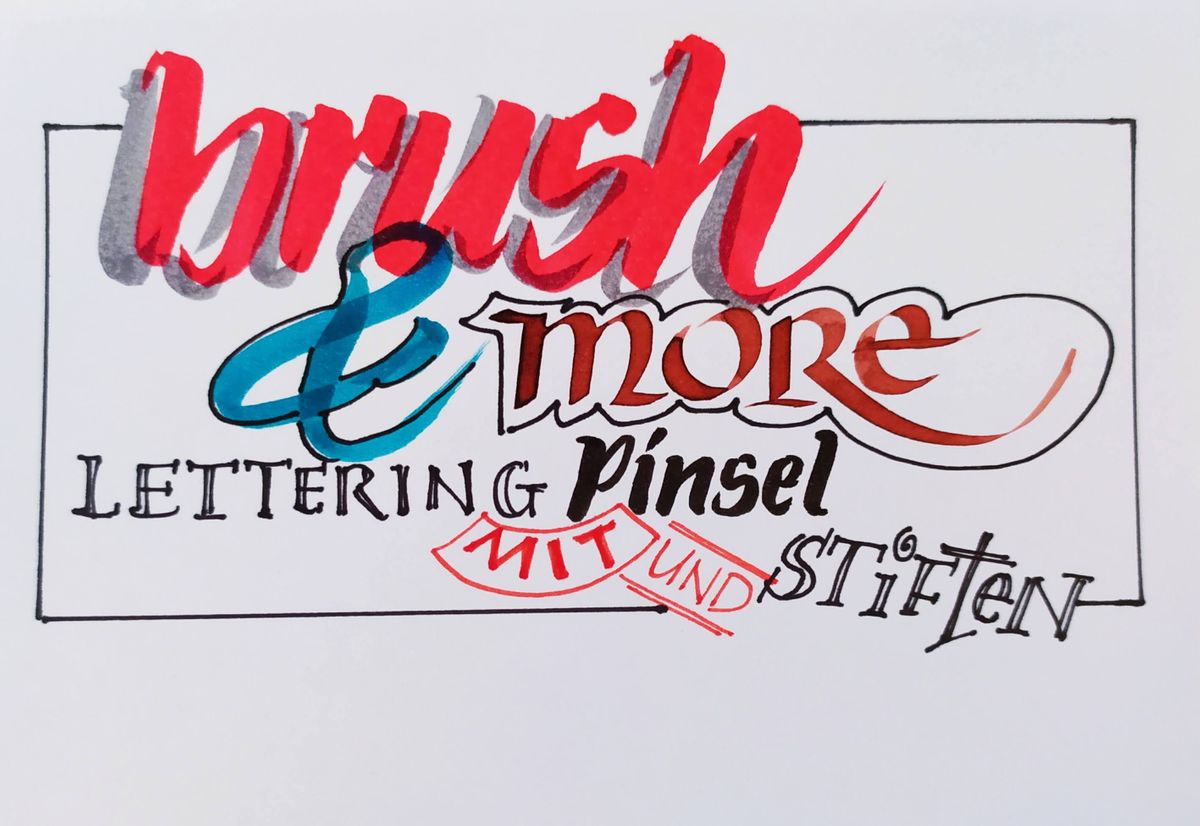
Besonders bei den geschwungenen schriftarten gibt es viele buchstaben in unzähligen varianten. Das klingt etwas nach vokabeln lernen und genau so ist es auch.
Kalligraphie schriftarten lernen. Bereits vor jahrhunderten gab sie der menschheit weltweit die. Dazu ist es wichtig nicht nur die striche und linienstärken genau zu studieren sondern auch die reihenfolge der strichführung zu beachten. Die oben beschriebenen werkzeuge und materialien reichen aus um sich erst einmal in die kunst des schönen schreibens einzuarbeiten.
Sie müssen keine vorkenntnisse mitbringen wenn sie die kalligraphie lernen wollen. Die kalligrafie mit einer pinselspitze macht sehr viel spaß erfordert jedoch etwas übung. Wenn du dir diese frage gerade stellst bist du hier genau richtig.
Deshalb ist es ratsam zunächst einige striche mit mehr und weniger druck zu zeichnen bevor man mit dem üben des alphabets beginnt. Jeder hat schon von ihr gehört und über ihre schönheit gestaunt die kalligraphie ist überall auf der welt beliebt und das schon seit jahrtausenden. Du kannst sie in allen bereichen einsetzen von websites über poster bis hin zu inspirierenden sprüchen.
Deine größte herausforderung wird es nun sein verschiedene schriftarten und buchstaben variationen auswendig zu lernen. Das wort kalligraphie korrekt ist auch kalligrafie und calligraphy en stammt aus dem griechischen und bedeutet die kunst des schönen schreibens. Ich werde dir die grundlagen zeigen und die wichtigsten dinge näher bringen damit du alles nötige weißt um kalligraphie schreiben zu lernen.
Schreiben ist nicht einfach ein mittel zum darstellen von gedanken die eigene handschrift kann auch ein wesentliches gestaltungselement sein. Für anfänger ist es aber ratsam zusätzlich kalligraphie. Ich werde dir zeigen wie du deinen stift vorbereitest und sauber machst werde dir zeigen welches papier am besten ist und du kannst dir kostenlos arbeitsblätter für drei.
Kalligraphie schriftarten sind ideal als blickfang und eignen sich vor allem in überschriften oder als statement schriftart. Kalligraphie lernen erste schritte. Was früher eine art der kommunikation war wird heute wo ein großteil der.
Kalligraphie lernen und schöne schriftarten gestalten was sie brauchen autor. Kalligrafie grundlagen lernen. Um kalligraphie schriften zu lernen benötigt man vorlagen die solange exakt reproduziert werden bis vorlage und abschrift haargenau übereinstimmen.
So lernen sie die grundtechniken der kalligrafie und des handletterings das einmaleins der kalligraphie. Doch wie komme ich mit meiner handschrift zu ausdrucksvollen kreativen ergebnissen.